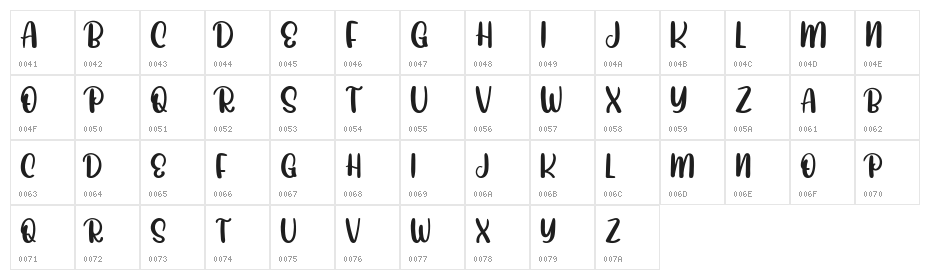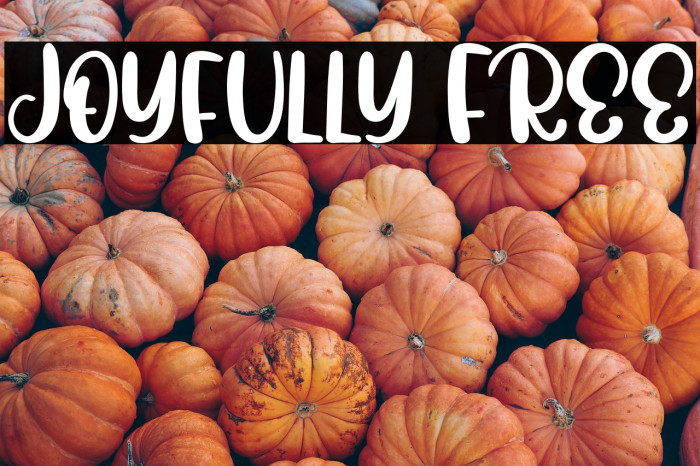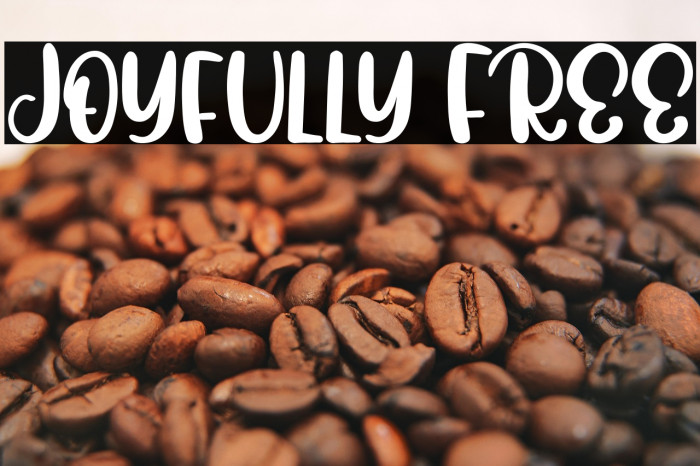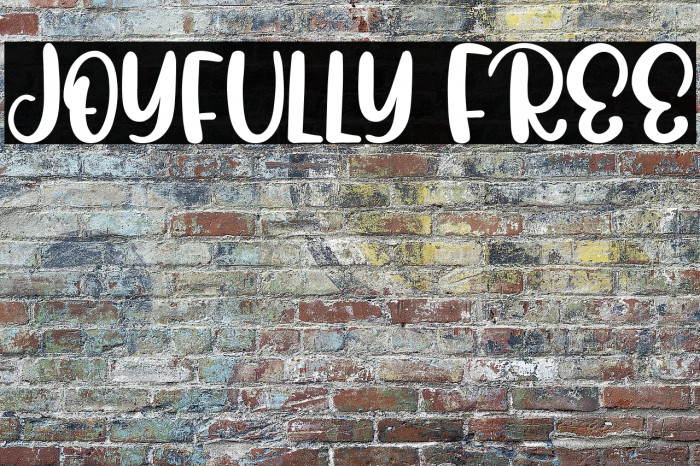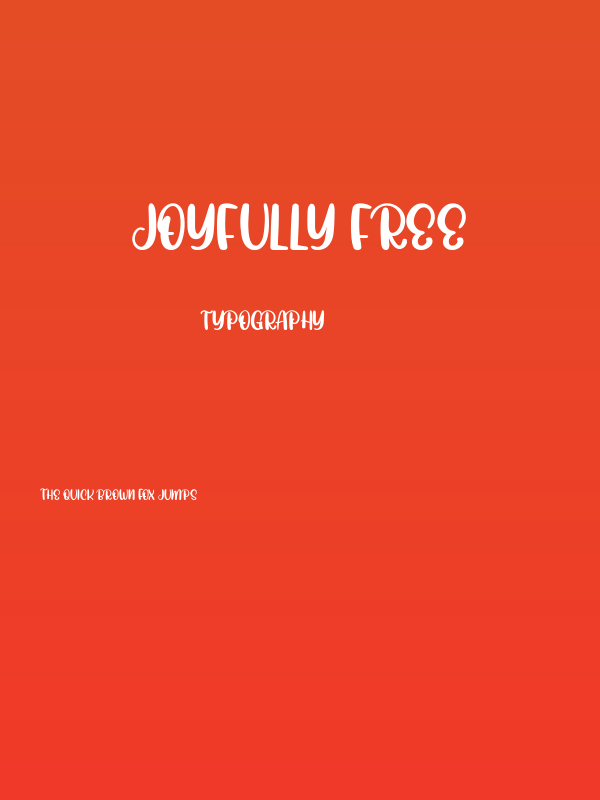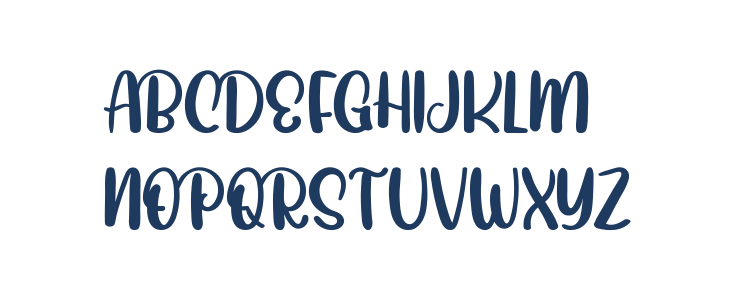
Joyfully FREE Font
| Gesamtstil | Playful |
| Anwendungsfall | Logos, Headlines, Invitations |
| Vorgeschlagene Projekte | Ideal for greeting cards, invitations, playful branding, and social media graphics. |